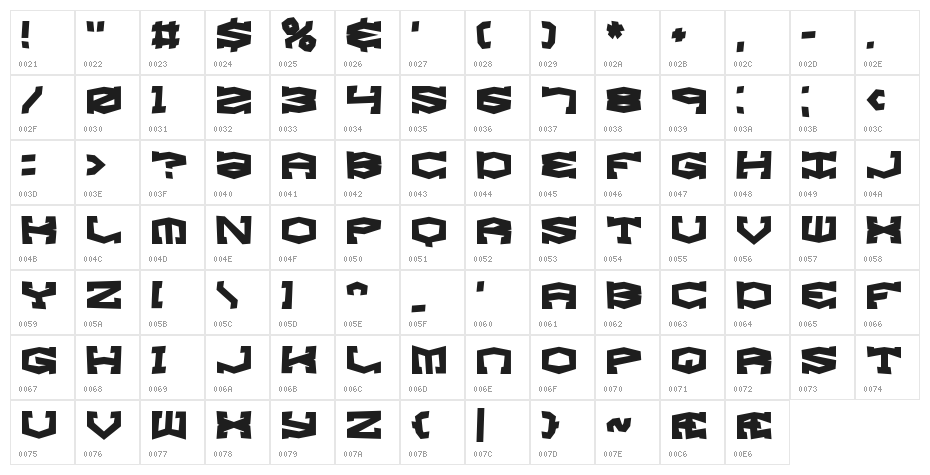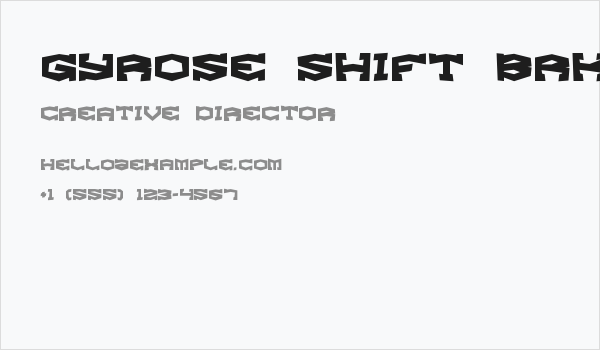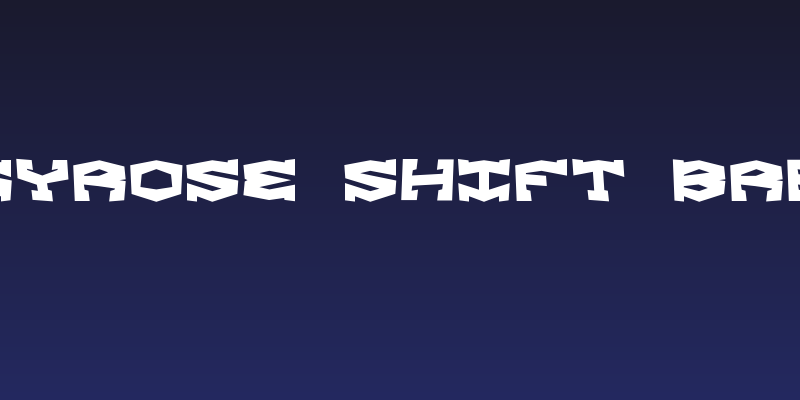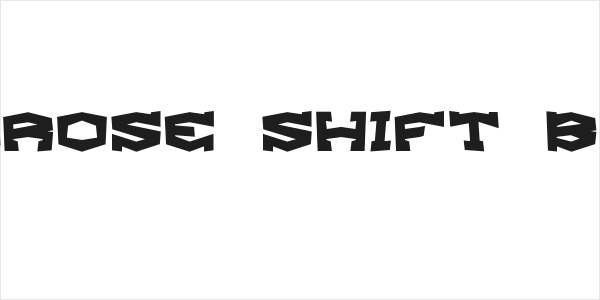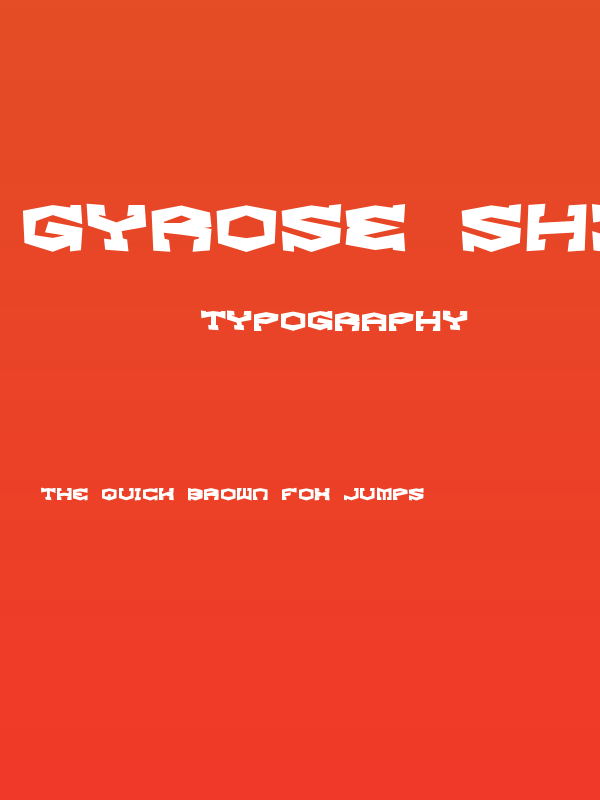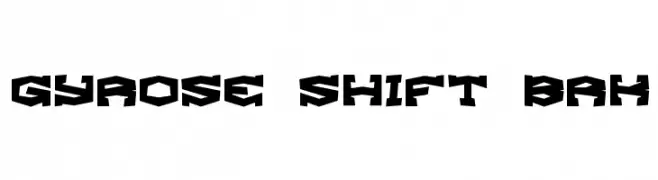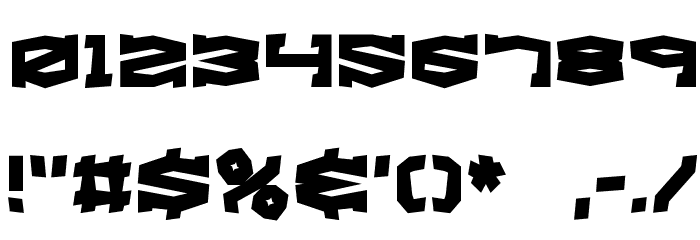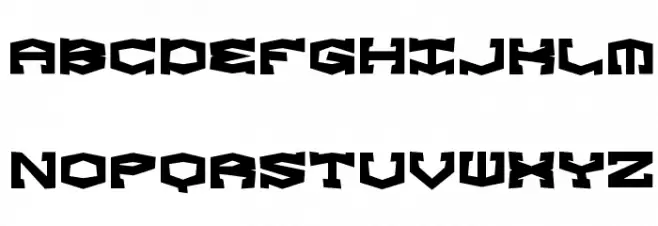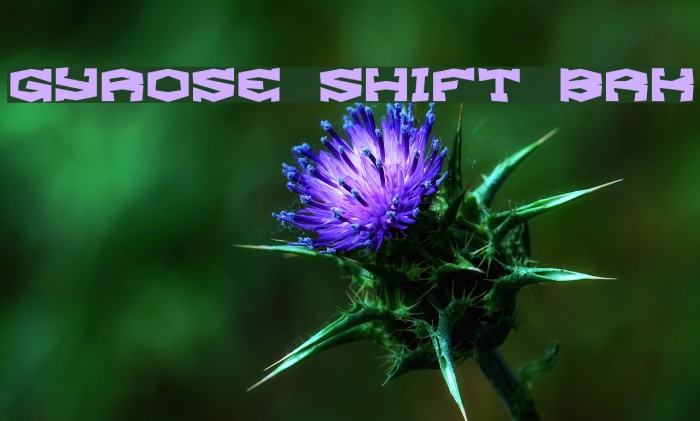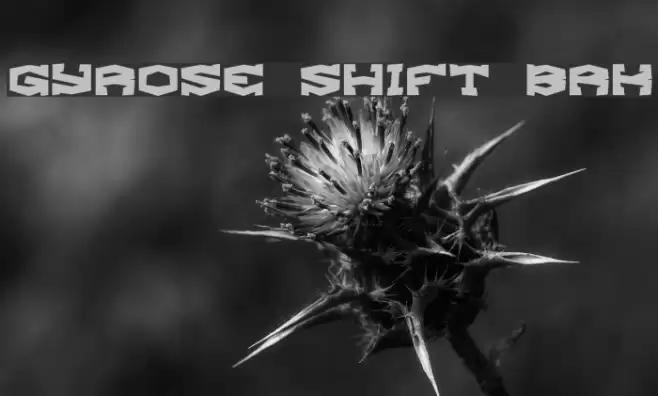
Gyrose Shift BRK Font
| Proyectos propuestos | Ideal for sci-fi themed designs, video game graphics, posters, and branding that requires a modern edge. |